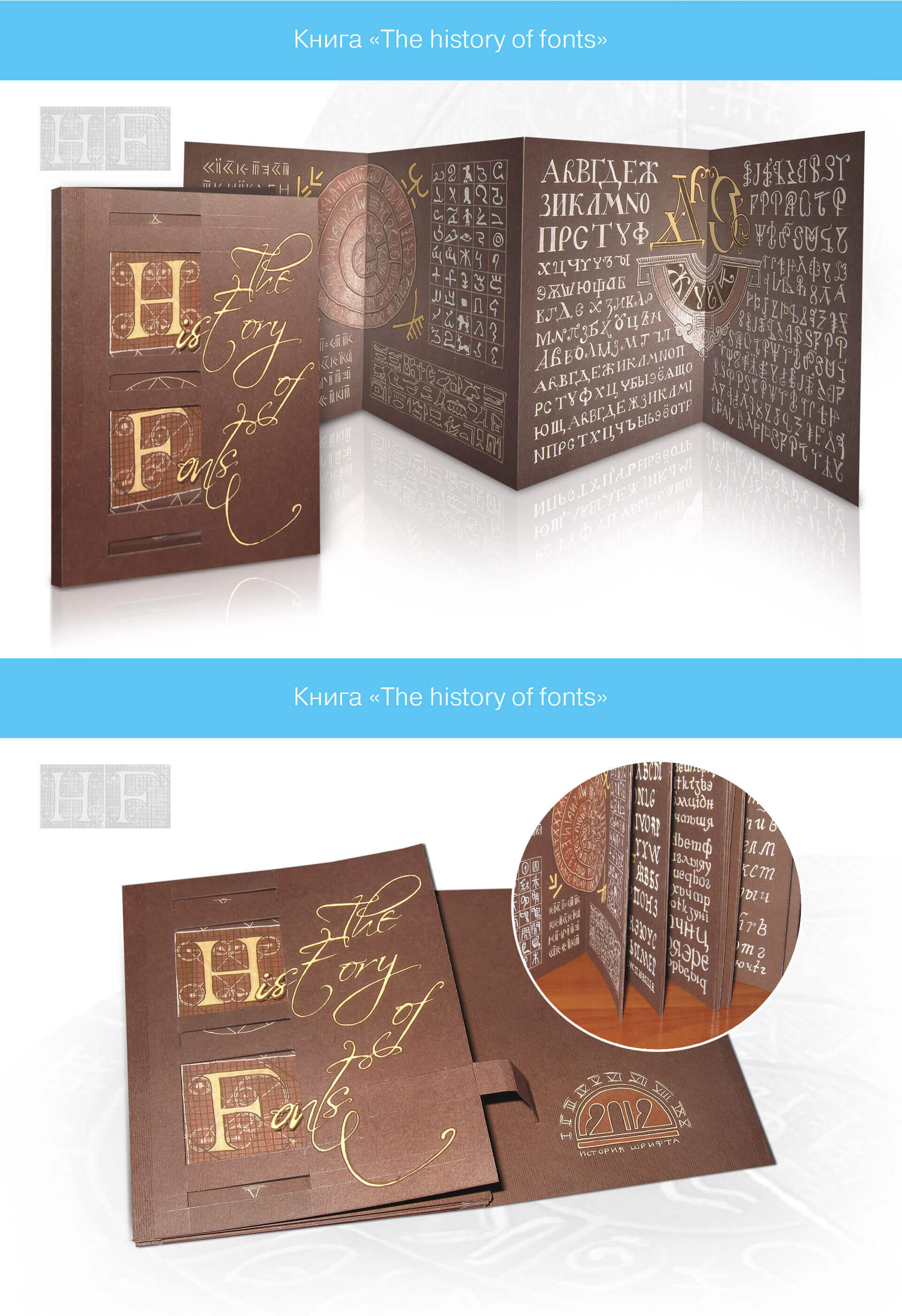
Książka „History of fonts”
Opłata dla studentów szkolnictwa wyższego w kierunku „Kalygrafia” i „Typografii”.Zadaniem jest:
Opracowanie projektu książki "Historia liter" od 1 do 10 wieku.Tworzenie niezwykłej książki według formy i wypełnienia.Wpisy muszą być pisane ręcznie, aby jak najczystsze przekazać kulturę pisania starożytnych czasów.Rozstrzygnięcie :
Zadanie polega na tym, aby na każdej stronie zawierać określony alfabet litery.Rysunek liter płynnie przechodzi po historycznej łańcuchu, a integralność kompozycji jest zachowana zarówno w jednym odcinku, jak i w trakcie rozłożenia książki w całości.Książka rozwija się jak harmonia.Takie podejście zostało stworzone tak, aby książka mogła być rozłożona i przeanalizowana historią tworzenia czcionek w określonym czasie.Na pokrywce znajduje się wycięcie i przejrzysty film.Na filmie pojawia się napis, w ten sposób tworzy się wizualnie efekt 3D.To sprawia, że powłoka jest wyjątkowa, kreatywna i pamiętna dla użytkownika, zwłaszcza gdy bierze ją w ręce i odczuwa, z jakich materiałów jest ona stworzona.